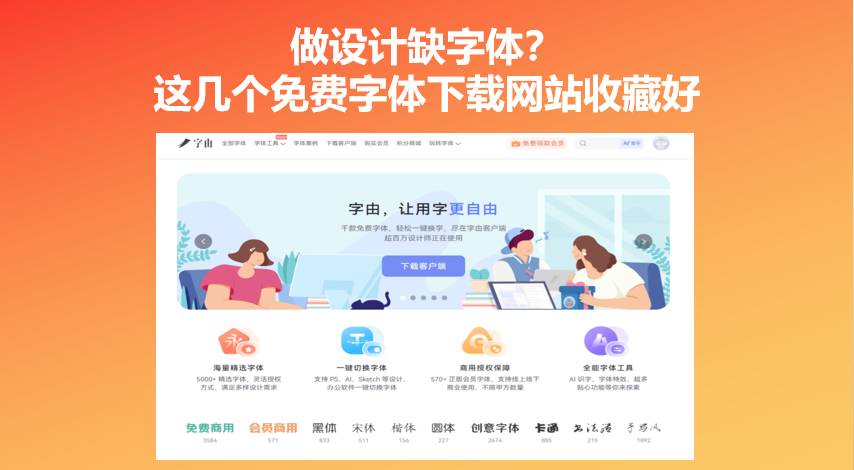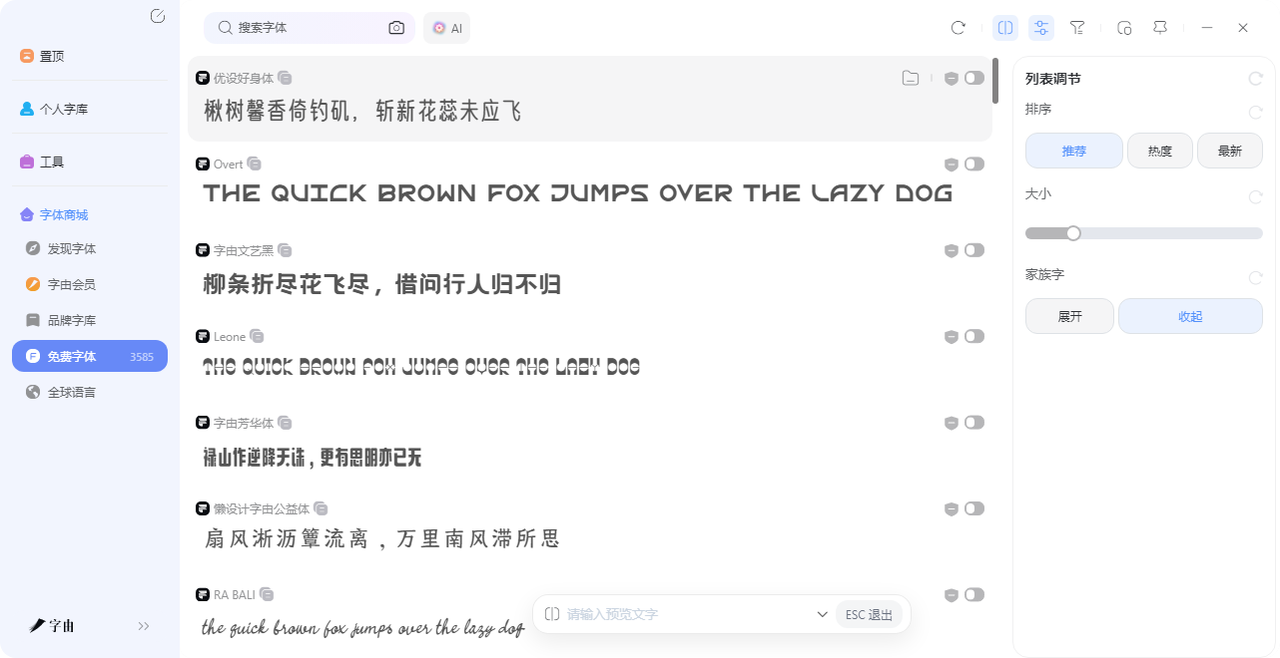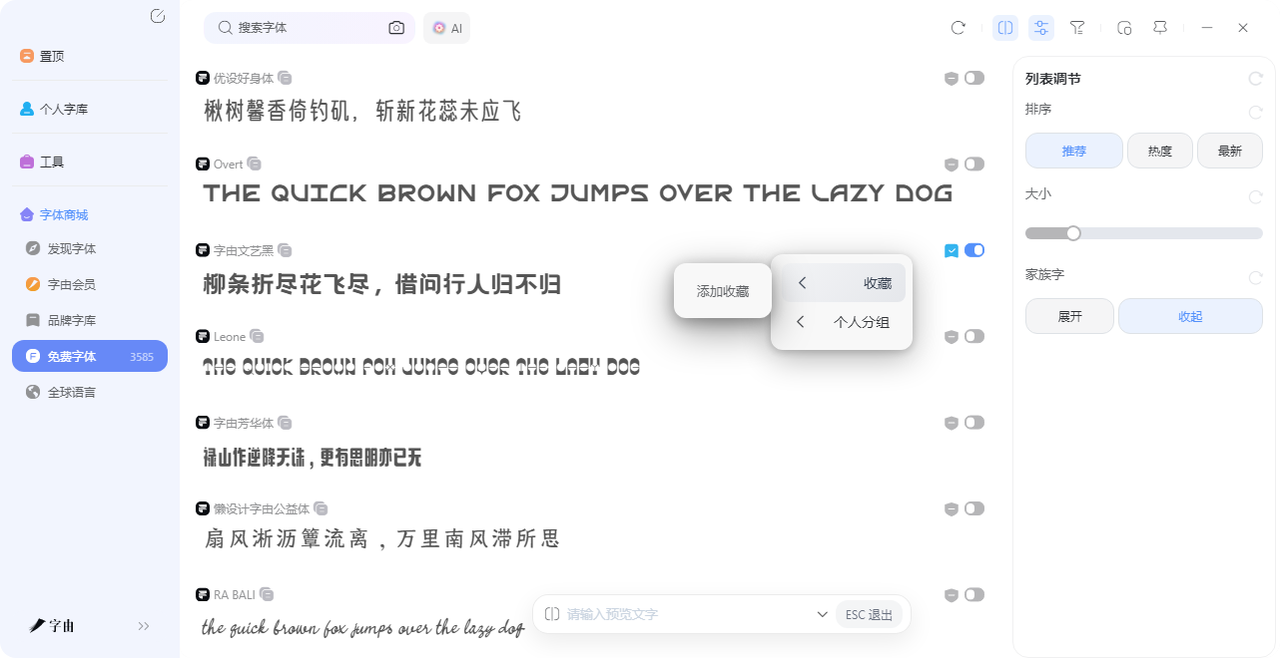
做设计缺字体?这几个免费字体下载网站收藏好
做设计这么久,电脑里的字体包换了一茬又一茬。刚开始不懂,见一个下一个,结果电脑里攒了上千款字体,真到用的时候反而不知道选哪个。后来慢慢摸出门道:好用的免费字体下载网站推荐,其实不用多,几个够用的就行。今天就把我私藏的5 个免费字体下载网站分享出来,从国产神器字由到国外老牌平台,每个都亲测好用,需要的直接收藏。
入行那会儿,最怕的不是没灵感,而是找到一款好字体,下载下来才发现“仅限个人使用”。后来用上字由,这种尴尬少了很多。它最大的好处不是字体多,而是每一款都标得清清楚楚——哪些能商用,哪些只能个人用,一目了然。下面我会告诉大家如何快速找到字由的免费可商用字体库:
打开字由,筛选栏直接点“免费商用”,3585款免费字体下载网站的资源就出来了。想找国风字体,点“中国风”;想要手写感,点“手写体”;拿不准风格,就看使用次数——“字由文艺黑”1436万次,“优设好身体”503万次,这些数字意味着很多人替你试过了,踩坑概率低得多。
如果你看中了一款字体,点进去有个预览框。把你想用的文字输进去,比如“春日来信”“开业大吉”,字体会自动用你的文案展示效果。不用下载,不用安装,看一眼就知道合不合适。确认之后,在PS里选中文字图层,回到字由点一下字体,文字就换好了。不用重启软件,不用等。
最后我推荐几个我常用的免费字体:
- 优设好身体:字形方正,做画册内页、公众号配文很稳,不抢眼但耐看。
- 字由文艺黑:既有黑体的稳重,又带一点手写感。做海报标题、品牌Logo,或者需要“正式但不死板”的感觉时,用它很对味。
- 沐瑶软笔手写:圆润治愈,做亲子类海报、手账内容、温暖治愈的社交媒体配图,用它很出片。
- 点字浅夏体:清新手写,做旅行vlog封面、生活记录类标题,很加分。
最主要的是,字由还支持个人云字库,可以把常用字体上传到云端。新电脑登录账号,直接就能用。不用U盘拷来拷去,也不用担心字体丢失。除了这些,字由还有“品牌字库”专区,汉仪、蒙纳、Aa字库这些老牌厂商都在,想找高品质字体的时候直接逛这里,每一款都拿得出手。
2、Befonts
Befonts是我常逛的免费字体下载网站之一,首页就是“Most Recent Free Fonts”,能看到最新上架的免费字体。最近更新的有“Srame Font”(优雅衬线)、“Old String Font”(复古)、“Evaco Font”(科技感)、“Gamlowfei”(签名体)等。
每款字体都标注了风格标签,比如Elegant、Vintage、Futuristic、Script,方便快速判断适不适合。如果你喜欢尝鲜,想找最近刚出的免费字体,这里很方便。它家还有一个“Premium Fonts”板块,偶尔会有打折活动,需要高品质商用字体的时候可以关注一下。“Most Recent Free Fonts”这个板块我经常翻,每周都有新字体上架。有时候能淘到刚出的热门款,比别人早用上,做出来的设计也不容易撞款。“Evaco Font”那款科技感字体我试过,做数码产品海报很合适。“Gamlowfei”签名体用在个人名片上也挺有范儿。它家字体虽然免费,但商用前最好还是看一眼授权说明,大部分标了“Free for commercial use”的就可以放心用。
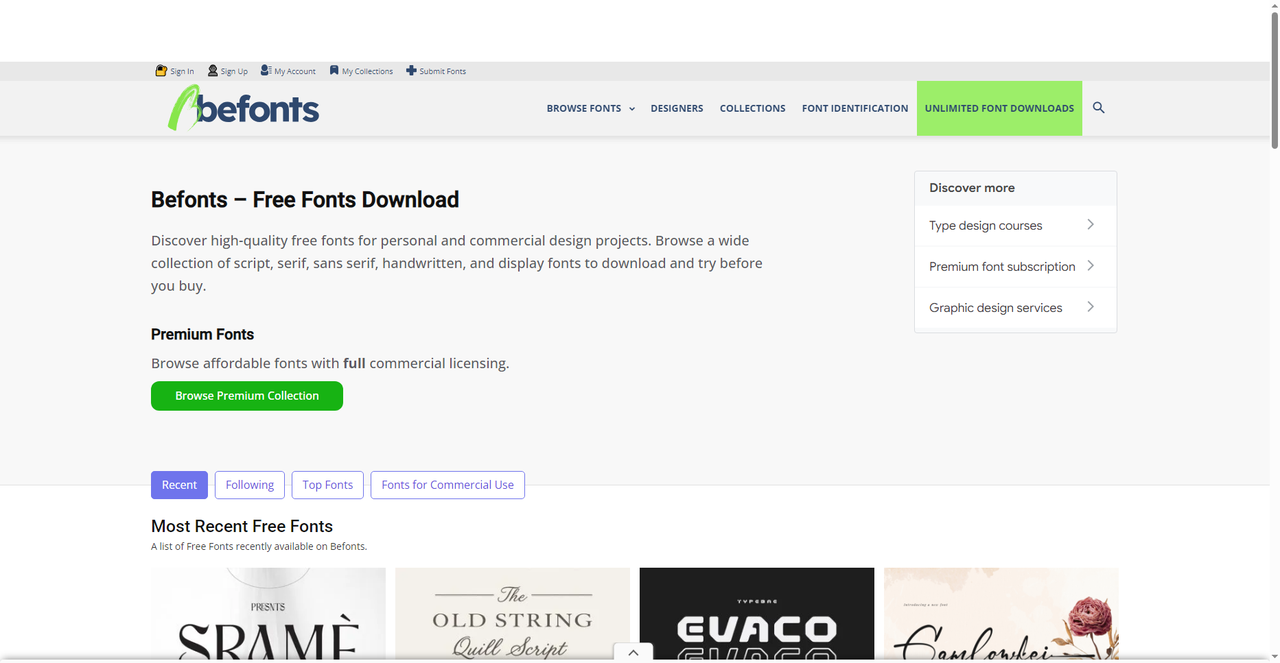
3、Cufon Fonts
Cufon Fonts是老牌字体站,分类很标准。从截图看,它收录了Helvetica字体家族——Helvetica、Helvetica Neue、Neue Helvetica BQ、Helvetica Neue LT Pro,总共加起来几十种字重。如果你需要经典的、经得起时间考验的字体,来这里找比较靠谱。下载前可以看看每款字体的样式预览,Helvetica这种经典字体,做品牌、做海报,用几十年都不会过时。它家的“专题合集”功能也挺实用,比如“Cinematic Fonts”“Magazine Fonts”这些,按主题分类,找起来很方便。而且它家的“Helvetica Neue LT Pro”有51种字重,做品牌VI的时候一套就够了。
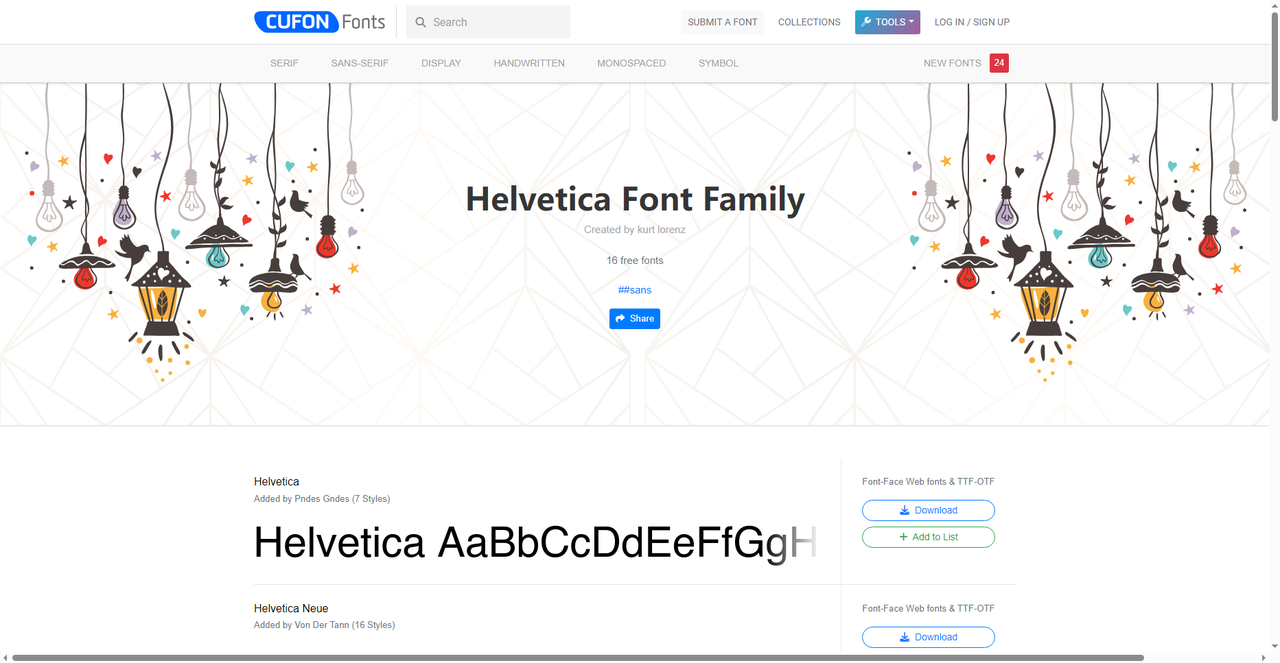
4、FontZone
FontZone的首页写着“Over 50,000 Free Fonts”——5万多款免费字体。它按字母顺序和风格做了分类:3D、Fancy、Sans Serif、Script、Graffiti、Handwriting、Pixel、Typewriter、Western……你想得到的风格基本都有。首页推荐了几款热门字体,比如“ADIDAS FOOTBALL 2002”(运动风)、“Coorgi-Cox”(手写)、“Organo”(无衬线)。每款字体都有下载次数,可以帮你判断受欢迎程度。下载前记得看一眼授权说明,有的是免费个人使用,有的是免费商用。它家的“按字母顺序”分类很直观,知道字体名字的话直接跳转,不用一页页翻。而且下载次数这个指标很实用,次数高的基本都是经过很多人验证的。“Western Fonts”这个分类我也经常看,做西部风格的海报或者复古主题的设计,从这里挑字体很对味。“Coorgi-Cox”手写体我收藏了,做手账标题的时候经常用。“ADIDAS FOOTBALL 2002”运动风字体,做体育类海报很对味。下载次数高的字体确实好用,踩坑概率低。
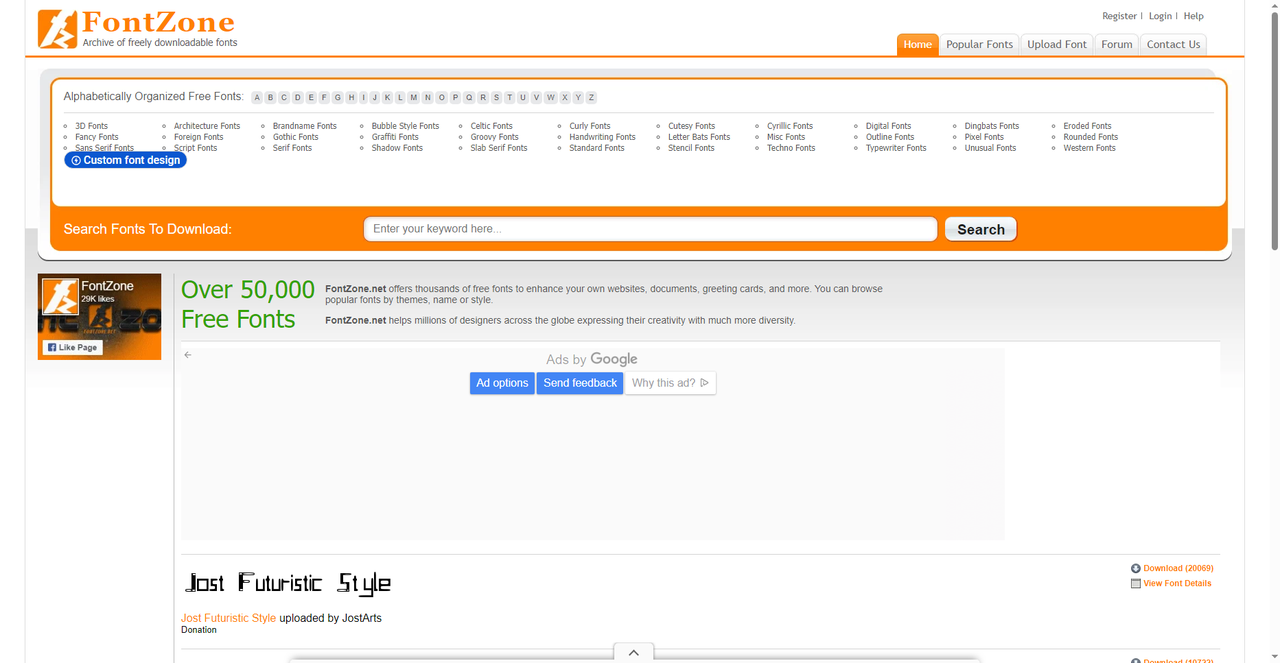
5、DaFont
DaFont是我最早知道的免费字体下载网站,运营了二十多年。它的分类非常传统但实用:Fancy、Fire Ice、Foreign look、Techno、Gothic、Basic、Script、Dingbats……每个大类下面还有细分,比如Fancy下面有Cartoon、Comic、Groovy、Old School、Western、Eroded、Distorted、Horror。首页会展示最新上传的字体,比如“Welcome Darling”“Simple Create”“Geraldyn Brushko”等。每款字体都有详细的安装说明和授权标注。DaFont的字体多为个人免费使用,商用需要仔细看授权,但作为找灵感的网站,它一直很靠谱。它家的“最近添加”板块更新很快,经常能看到刚上架的新字体。有时候能淘到一些很前卫的风格,做实验性设计的时候用得上。
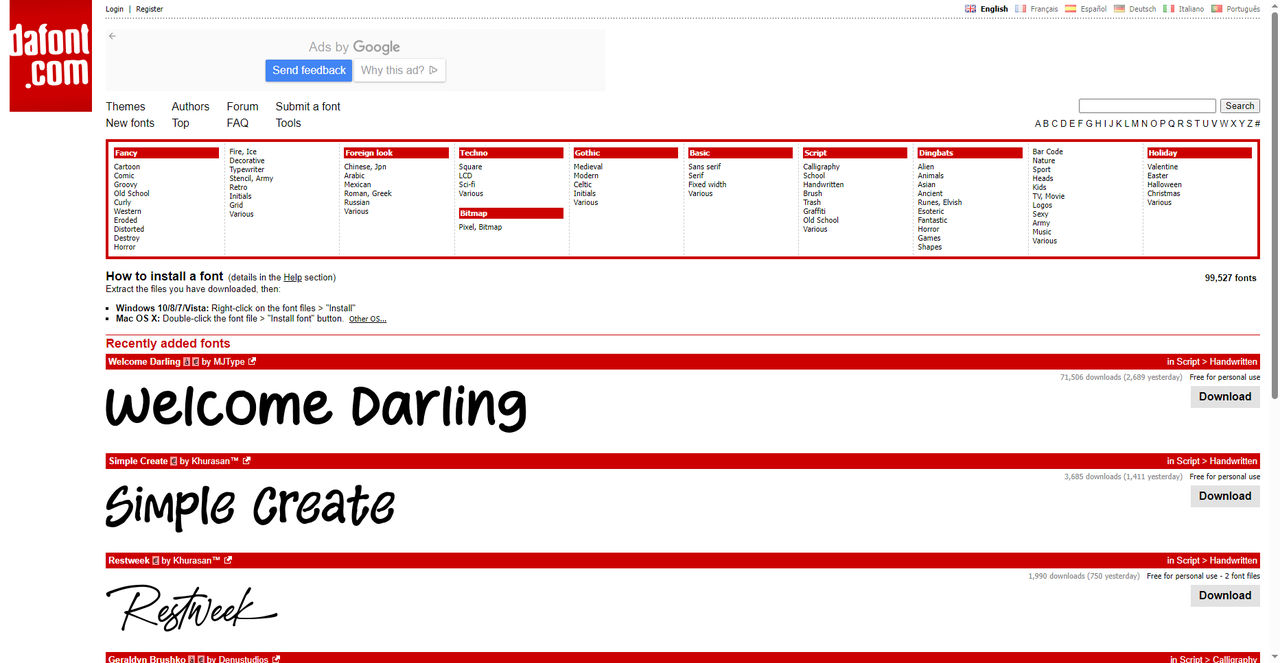
这几个免费字体下载网站,我平时用的频率不太一样。Befonts 适合追新,Cufon Fonts 适合找经典,FontZone 胜在字体总量多,DaFont 分类最全。但字由是我打开次数最多的——可能是因为用起来更加便捷,因为不用下载安装包,不用重启软件,点一下字体就能用了。如果你也经常为找字体发愁,不妨试试字由,看看会不会也很顺手。